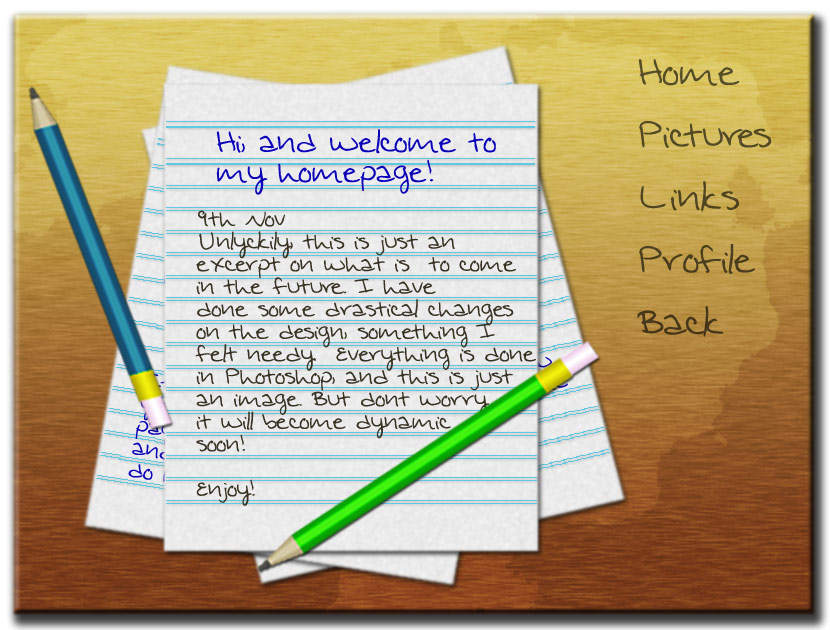
Anterialis Skrevet 9. november 2006 Hva skjer om jeg bruker en font når jeg lager hjemmeside, som er veldig sjelden --> ingen andre har? Vil de ikke se hva som står der da? På forhånd takk =)
Erik B. Skrevet 9. november 2006 Da vil teksten bli vist med font typen Times New Roman
Haraldson Skrevet 10. november 2006 (endret) Da vil teksten bli vist med font typen Times New Roman Ikke nødvendigvis. Det kommer helt an på hva man har satt som standardfont i sin nettleser. Videre kan jeg si at du bør angi fonter på følgende måte; p { font-family: font1, "font med flere ord i navnet", font2, sans-serif; } Da kan nettleseren være enda mer nøyaktig - finnes ingen av de tre spesifiserte fontene, vil nettleseren finne fram fonten som er satt som standard sans-serif-font. sans-serif kan byttes ut med følgende verdier (som samsvarer med fontene du tidligere i lista lister opp, og som sier noe om den generelle stilen på elementet du stilgir) - serif, monospace, fantasy og cursive. Endret 10. november 2006 av Mr.Berg
Anterialis Skrevet 10. november 2006 Forfatter Skrevet 10. november 2006 (endret) Ok, fordi kjedet meg litt i går, og lagde et cartoon-inspirert bilde, som jeg fant ut at jeg kan lage en nettside av. Her _må_ jeg jo nesten har denne spesielle fonten, eller er det fonter dere vet ligner som er standard? OT: Hvordan lager jeg et sånt lite bilde sånn at dere må trykke for å få opp fullversjonen? Endret 10. november 2006 av w3p
Erik B. Skrevet 10. november 2006 (endret) Ok, fordi kjedet meg litt i går, og lagde et cartoon-inspirert bilde, som jeg fant ut at jeg kan lage en nettside av. Her _må_ jeg jo nesten har denne spesielle fonten, eller er det fonter dere vet ligner som er standard? OT: Hvordan lager jeg et sånt lite bilde sånn at dere må trykke for å få opp fullversjonen? 7257016[/snapback] Du kan jo ta i bruk Comic Sans, som ligner litt på den du bruker. Den er standard i Windows tror jeg! For å lage thumbnails på en enkel måte kan du bl.a gjøre det slik: <a href="stortbilde.jpg"><img height="300" width="300" src="stortbilde.jpg" alt="" /></a> Men denne metoden anbefales ikke da det kan ta _svært_ lang til å laste bildet dersom orginal bildet er stort. Den beste måten er å ta i bruk litt php for å lage små thumbnails! Endret 10. november 2006 av erixz